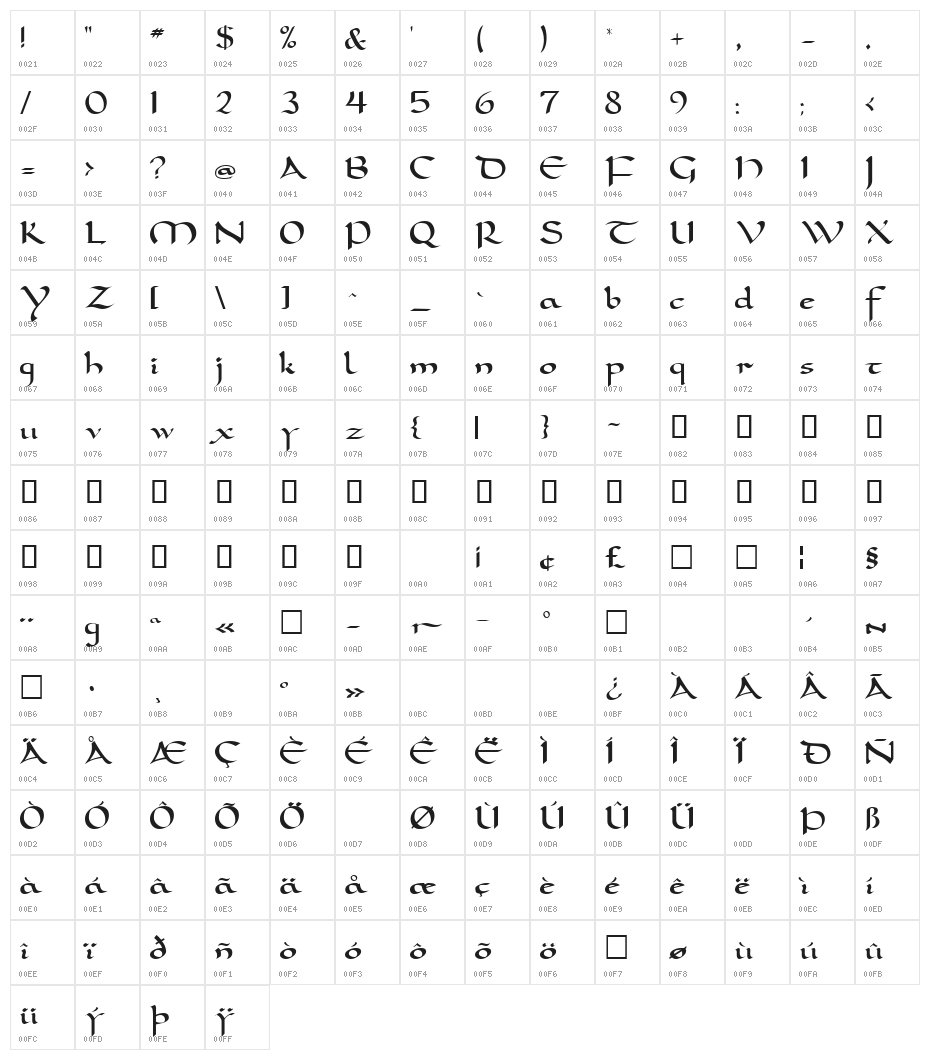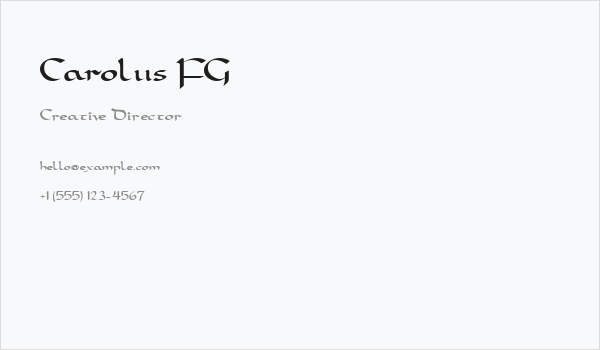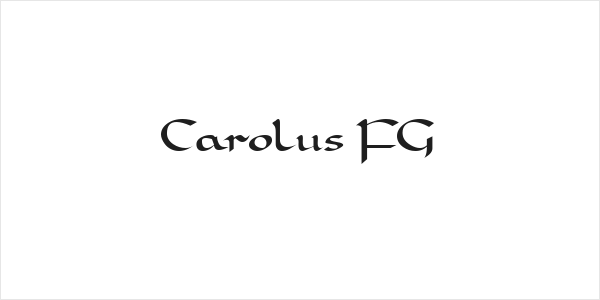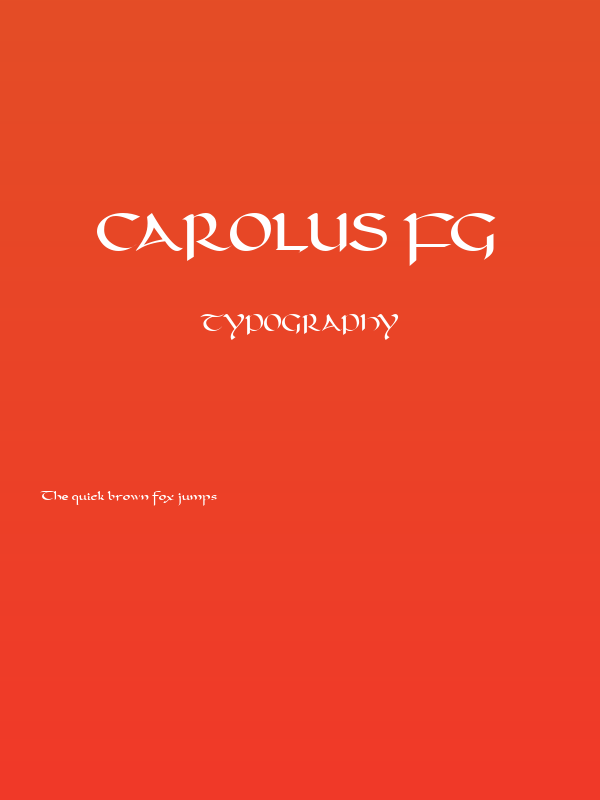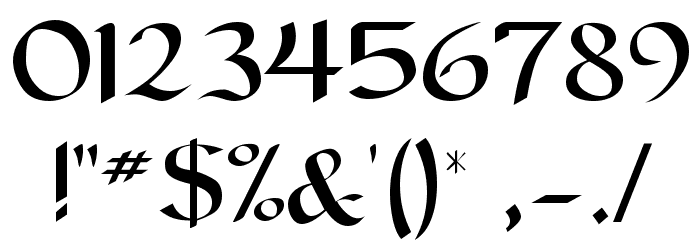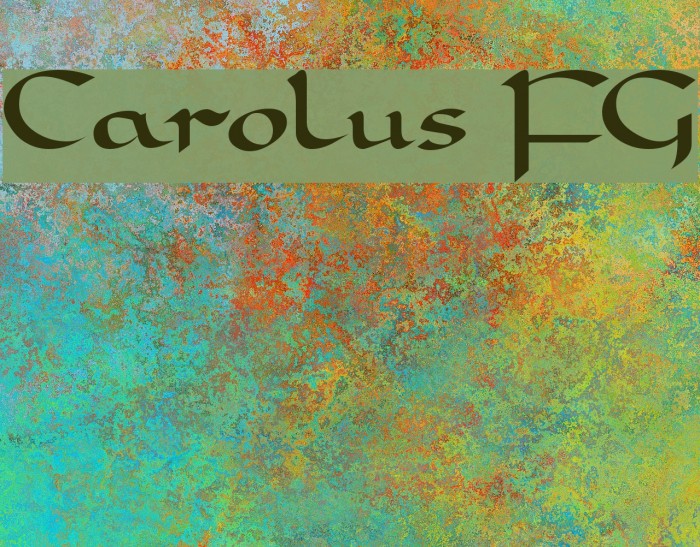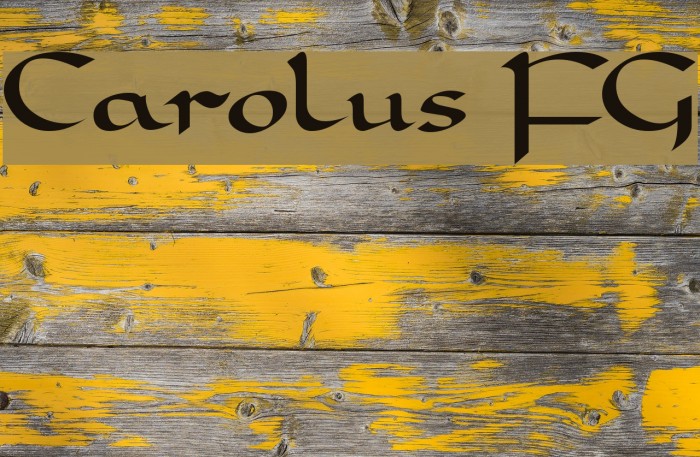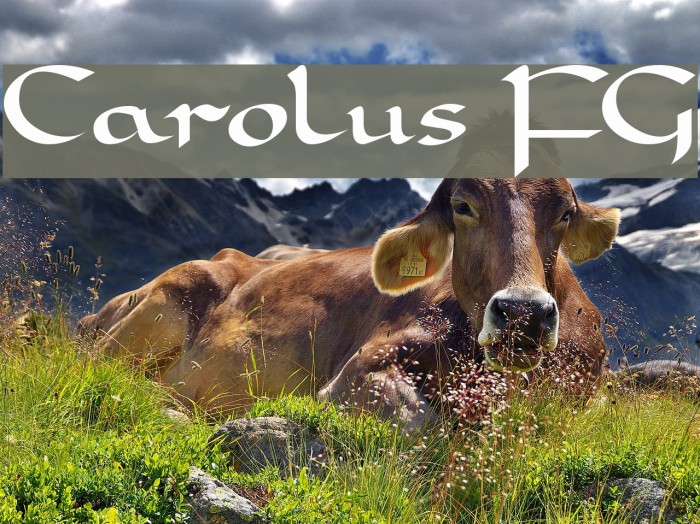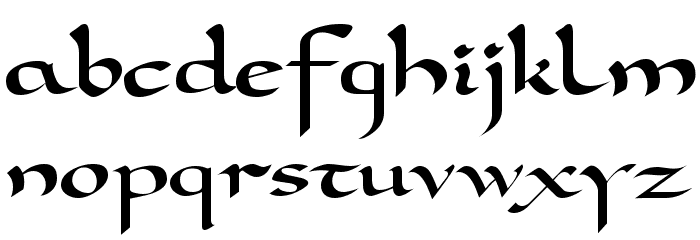
Carolus FG Font
| Caso d'uso | Headlines, Logos, Decorative text |
| Progetti proposti | Suitable for historical documents, medieval-themed designs, book covers, and branding that requires a traditional or gothic touch. |